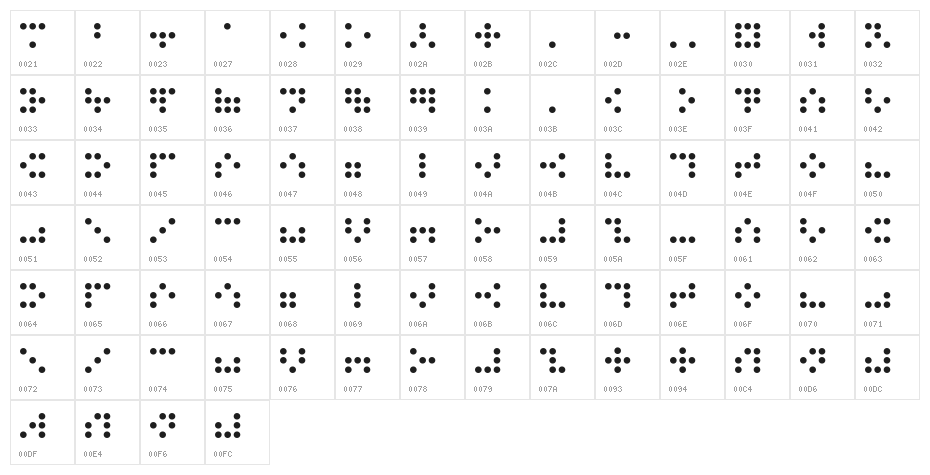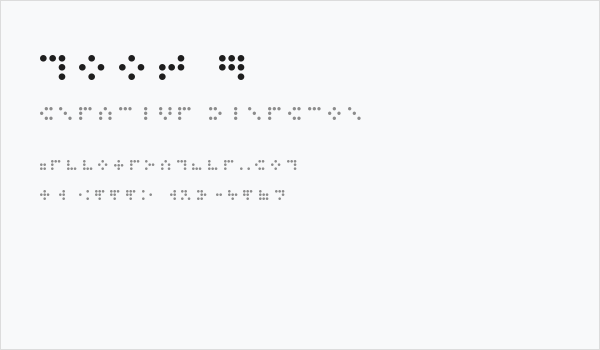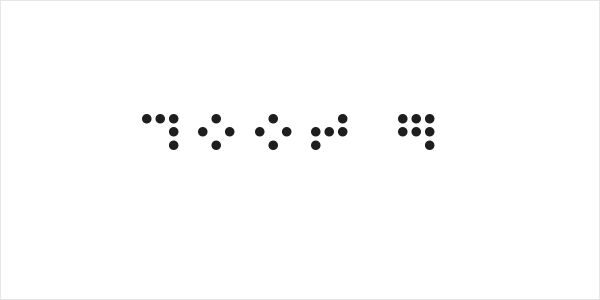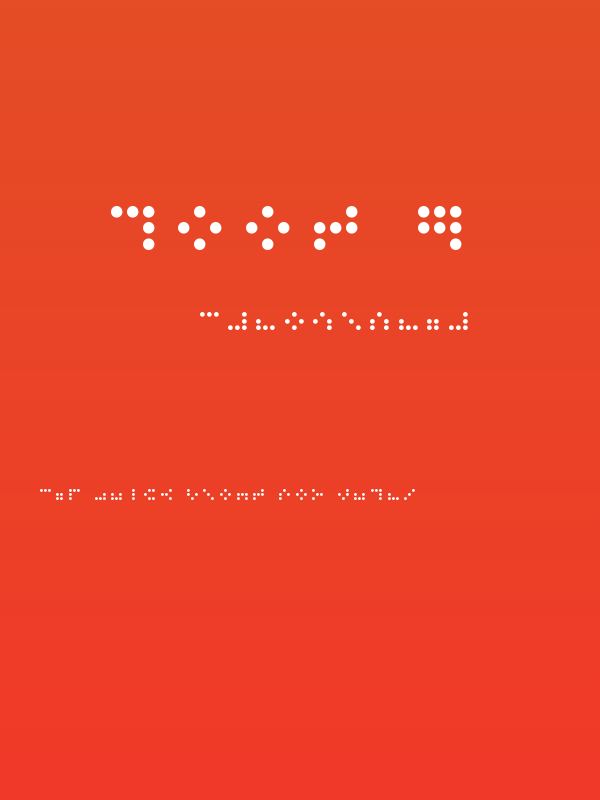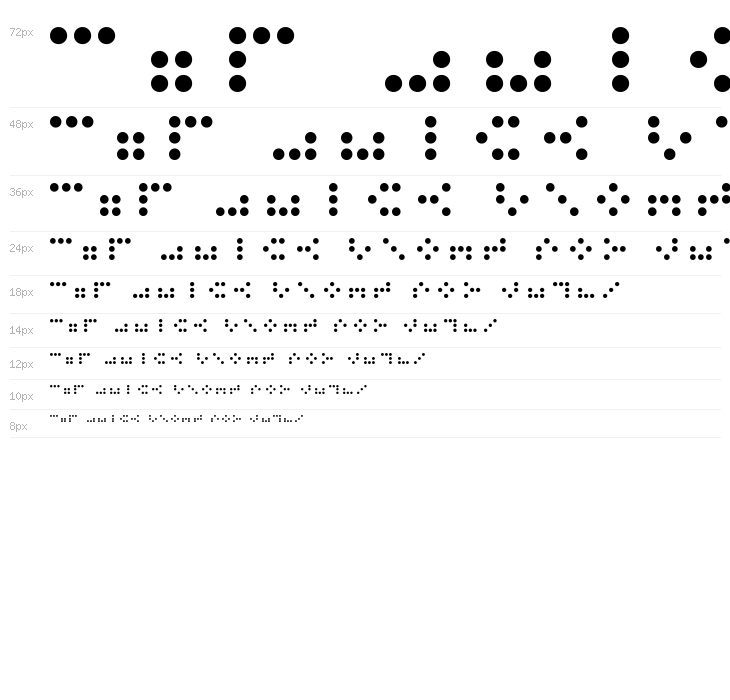
Moon 9 Font
| Version | Version 1.0 - the Moon Alphabet in 3x3 dots for use Braille technic |
| Gesamtstil | Functional |
| Anwendungsfall | Accessibility, Educational materials |
| Vorgeschlagene Projekte | Ideal for creating educational materials, signage, and books for the visually impaired. |